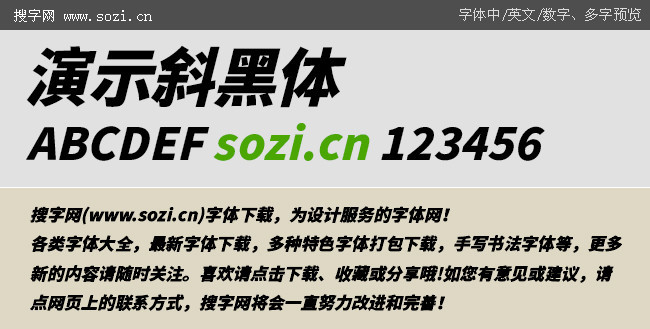
演示斜黑體
搜字網(wǎng)給大家提供一款演示斜黑體中文字體下載,演示斜黑體字體是一款傾斜狀的黑體藝術(shù)字體,字體筆觸粗實(shí),書(shū)寫(xiě)端正大氣,字體排版略顯傾斜,適合應(yīng)用于藝術(shù)設(shè)計(jì)、平面宣傳設(shè)計(jì)、網(wǎng)頁(yè)設(shè)計(jì)等廣告設(shè)計(jì)。